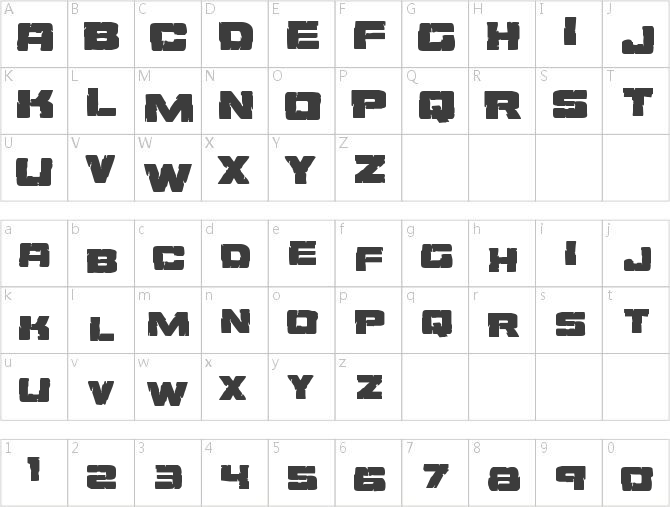
Ore-Crusher-Expanded 詳情頁
Ore-Crusher-Expanded字體字庫是一款讓人賞心悅目、百看不厭的英文字體,適合各類廣告和產(chǎn)品包裝設(shè)計應(yīng)用,字體大小0.07MB,格式為ttf字體,上傳用戶是華大文化傳媒,作者/版權(quán)方為未知